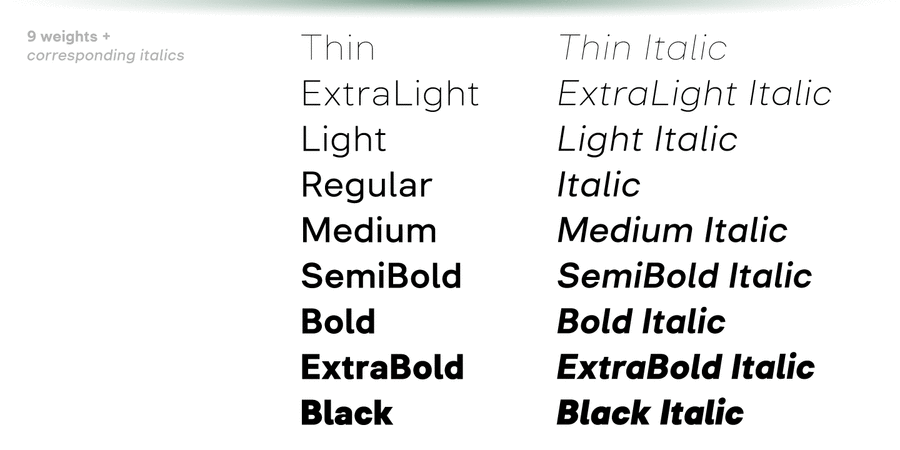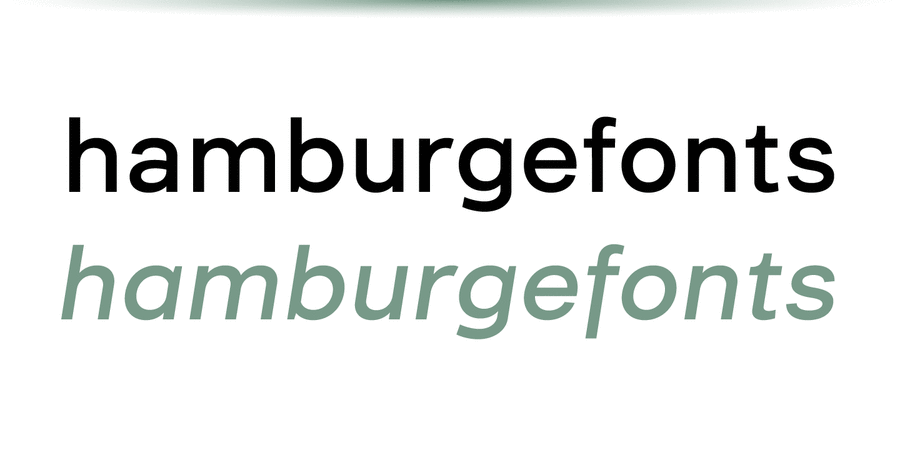
Нейтральний, але не безхарактерний гібрид геометричного гротеску та неогротеска. Шрифт розроблений для ідеальної роботи в UI/UX додатках і залишається читаним в найменших розмірах тексту. Шрифт Inerta можна налаштувати за допомогою декількох наборів альтернативних гліфів. Кирилиця містить альтернативні варіанти для болгарської кирилиці та української кирилиці. Гарнітуру розробив Андрій Константинов в студії Mint Type у 2021 році.
Асоціації з сімейством шрифтів InertaОсобистість і характер гарнітури:
мінімалістичний, чіткий, делікатний, чистий, легкий, прохолодний, свіжий, модний, тонкий, сучасний, лаконічний, ясний, рівний, якісний, невагомий, прозорий, логічний, точний, повітряний, скляний, гострий, дротяний, міський, статичний, худий, глобалізований, глобалістічний, крихкий, холодний, Простий, твердий, зрозумілий, доступний, елементарний, правильний, формальний, серйозний, стійкий, стабільний, самостійний, відповідальний, західний, діловий, спокійний, креслярський, інженерний, нейтральний, помірний, стандартний, невиразний, універсальний, розумний, байдужий, непомітний, ввічливий, значний, обов'язковий, солідний, сильний, важкий, переконливий, важливий, урбаністичний, надійний, залізний, сталевий, грубий, впевнений, потужний, строковий, наполегливий, мужній, різкий, робочий, промисловий, суворий, технічний, індустріальний, яскравий, помітний, щільний, активний, машинний, техногенний, тісний